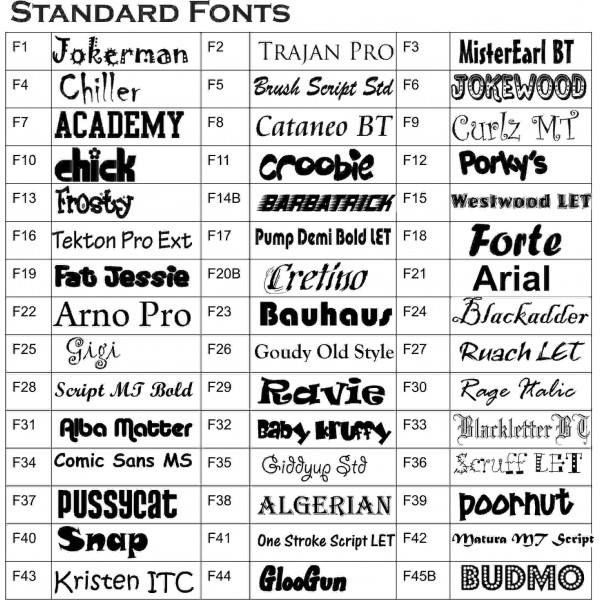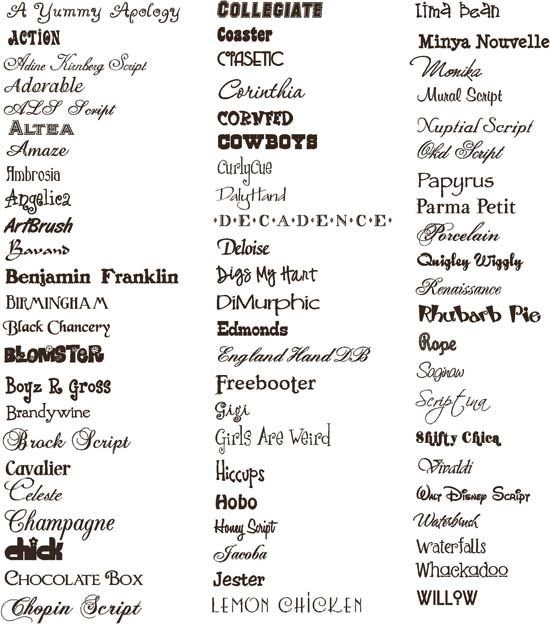
10 лучших шрифтов для дизайна электронной почты в 2022 году [и лучшие практики]
Вы не испытывали настоящей агонии, если никогда не читали рукописный рецепт врача. Ваша аудитория чувствует то же самое, когда читает содержимое электронной почты, написанное некачественным шрифтом.
В среднем люди 13,4 секунды тратят на чтение электронной почты. Последнее продлевается при выборе нечитаемых шрифтов. Более длительное время чтения приводит к разочарованию потенциальных клиентов, а это то, чего вы не хотите.
В этой статье обсуждаются 10 лучших шрифтов для электронной почты, чтобы их не только открывали, но и читали. Обязательно ознакомьтесь с лучшими практиками для шрифтов электронной почты в конце!
У нас есть для вас небольшое (читай: веселое) упражнение. Прочитайте следующий текст как можно быстрее.
Если вы чем-то похожи на нас, вам было нелегко читать отрывок.
Если бы он был написан удобным для чтения шрифтом, вы бы сразу поняли, что текст на самом деле является текстом известной песни Backstreet Boys «I Want It That Way».
От выбранных вами шрифтов зависит успех вашей кампании по электронной почте или нет. 70% читателей удалят электронное письмо в течение 3 секунд , если оно отображается или отформатировано неправильно.
Шрифты важны, поскольку они влияют на общее настроение письма. Как и цвета, шрифты имеют индивидуальные характеристики. Если электронное письмо, которое вы отправляете, направлено на сбор средств для ликвидации последствий землетрясения, выбор Comic Sans MS создаст впечатление, что вы не заслуживаете доверия.
Бренды поддерживают свои ценности и индивидуальность с помощью шрифтов, которые они используют. Вы никогда не увидите, чтобы Vogue отправлял электронные письма с текстом, написанным шрифтом, вдохновленным граффити.
В настоящее время доступно из более чем 200 000 шрифтов, из которых еще больше.
Все шрифты разделены на четыре семейства шрифтов на основе схожих дизайнов. Эти семейства шрифтов являются родительскими, в то время как другие шрифты, такие как Arial и Times New Roman, можно считать их дочерними.
Шрифты с засечками легко узнать по декоративным штрихам в конце каждой буквы. Они считаются традиционными, формальными, старомодными и надежными. Такие шрифты идеально подходят для заголовков и любого текста большего размера. Логотип Джорджио Армани написан шрифтом с засечками.
2. Без засечек 81% американцев предпочитают шрифты без засечек шрифтам с засечками. Как следует из названия, шрифты без декоративных штрихов называются шрифтами без засечек. Такие шрифты кажутся современными, чистыми и гуманистичными. Многие считают, что шрифты без засечек больше подходят для электронной почты, чем их аналоги. Логотип Google написан шрифтом без засечек.
Script Шрифты Script имитируют рукописный почерк.
Эти шрифты были вдохновлены каллиграфией и формальным письмом 17-го века и обозначают черты элегантности и классики. Хотя такие шрифты не идеальны для использования в электронной почте, они отлично подходят для творческих заголовков. Логотип Kellogg — популярный пример рукописных шрифтов.
Такой стиль шрифта более искусный, чем практичный. Декоративные шрифты легко узнать по их уникальному и нетрадиционному дизайну. Хотя мы рекомендуем использовать этот стиль экономно, декоративные шрифты считаются креативными, смелыми и модными. Логотип Fanta — забавный пример того, как выглядят декоративные шрифты.
Категории шрифтов электронной почты Теперь мы знаем четыре семейства, к которым принадлежат шрифты. Но что такое категории шрифтов для электронных писем? Электронные письма просматриваются на экранах дисплеев, будь то ноутбуки или мобильные устройства. Некоторые шрифты устанавливаются в системе, а другие размещаются на веб-сервере.
Место размещения шрифта напрямую влияет на то, как он будет отображаться для конечного читателя.
Шрифты, установленные на компьютере, называются системными. Последние называются безопасными веб-шрифтами (или электронной почтой), поскольку они выглядят так, как задумано, и хорошо работают у всех поставщиков услуг электронной почты. Эти шрифты подобны вредным привычкам, которые никогда не уходят из виду, как бы вы ни старались.
Хотя критики могут назвать их скучными, эти шрифты были разработаны, чтобы быть надежными. Содержимое электронной почты будет одинаковым для всех ваших подписчиков и для всех используемых почтовых провайдеров.
Веб-шрифты не устанавливаются в системе, а загружаются с веб-сервера. Поскольку он не является системным, шрифты должны поддерживаться веб-браузером человека и поставщиком услуг электронной почты .
Многие с осторожностью относятся к использованию таких шрифтов, поскольку нет гарантии, что содержимое будет выглядеть так, как задумано.
Решение этого? Резервные шрифты. Эти шрифты предварительно установлены в вашей системе и, следовательно, безопасны для электронной почты. Если человек использует старый браузер или браузер не совместим с веб-шрифтом, содержимое электронной почты будет отображаться с использованием резервного шрифта. Arial (без засечек) и Times New Roman (с засечками) — самые популярные безопасные веб-шрифты .
4. Аналитика
Возможно, Аналитика не является генератором шрифтов Google в традиционном понимании. Тем не менее, он расскажет вам о самых популярных шрифтах Google. Если вы хотите использовать самые популярные веб-шрифты, вы быстро узнаете, что Roboto находится в верхней части списка. В психологии есть так называемый эффект простого воздействия, который означает, что людям нравятся вещи, которые им наиболее знакомы.